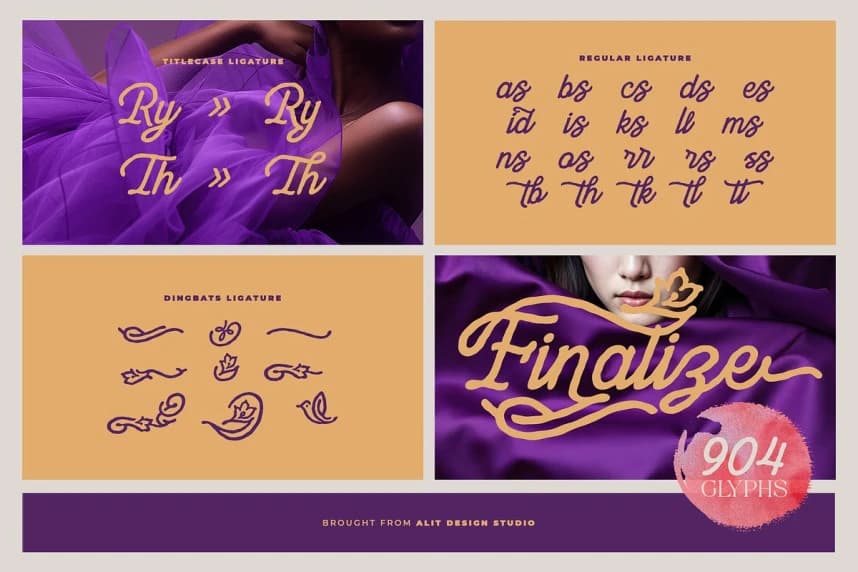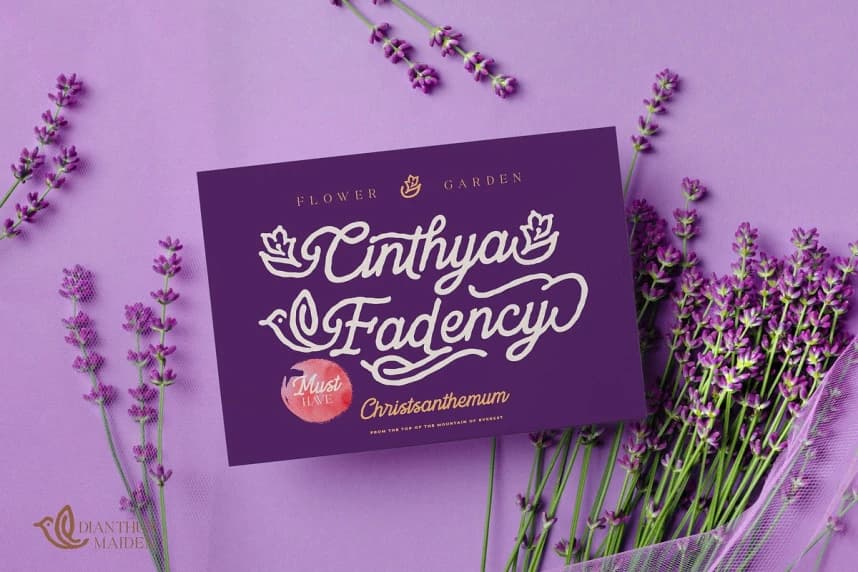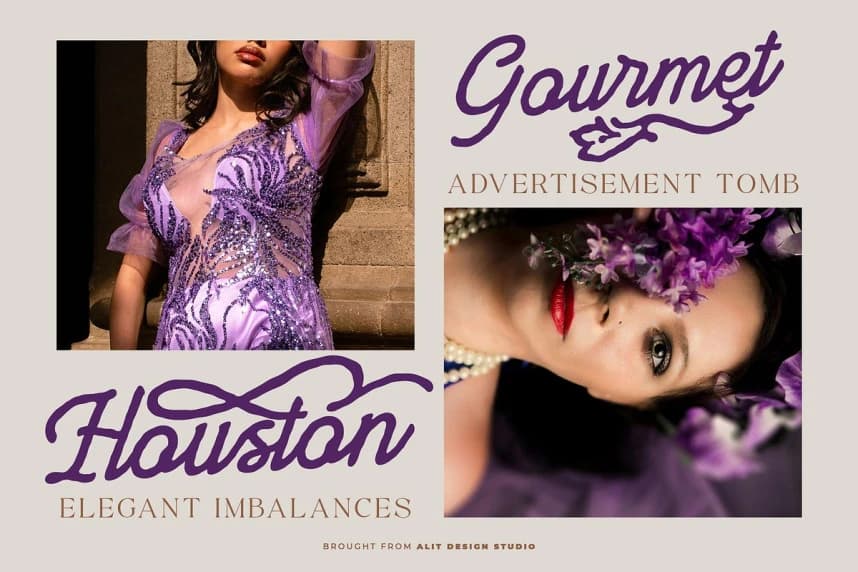
Dianthus Maiden Font
Dianthus Maiden Font, yaratıcı projelerinize zarif ve lüks bir dokunuş katmak üzere tasarlanmış, nefes kesici derecede zarif bir el yazısı fontudur. Akışkan, elle çizilmiş kaligrafinin özünü yakalamak için ustaca tasarlanmış bu yazı tipi, klasik sofistike ile modern botanik güzelliğini bir araya get
Dianthus Maiden Font, göz alıcı derecede zarif ve lüks bir el yazısı fontu olarak yaratıcı projelerinize zarif bir romantizm dokunuşu katmak üzere tasarlanmıştır. Akıcı, elle çizilmiş kaligrafinin özünü yakalamak için ustalıkla tasarlandı; bu yazı tipi klasik zarafeti modern botanik güzelliğiyle birleştirir.
Dianthus Maiden
Dianthus Maiden Regular